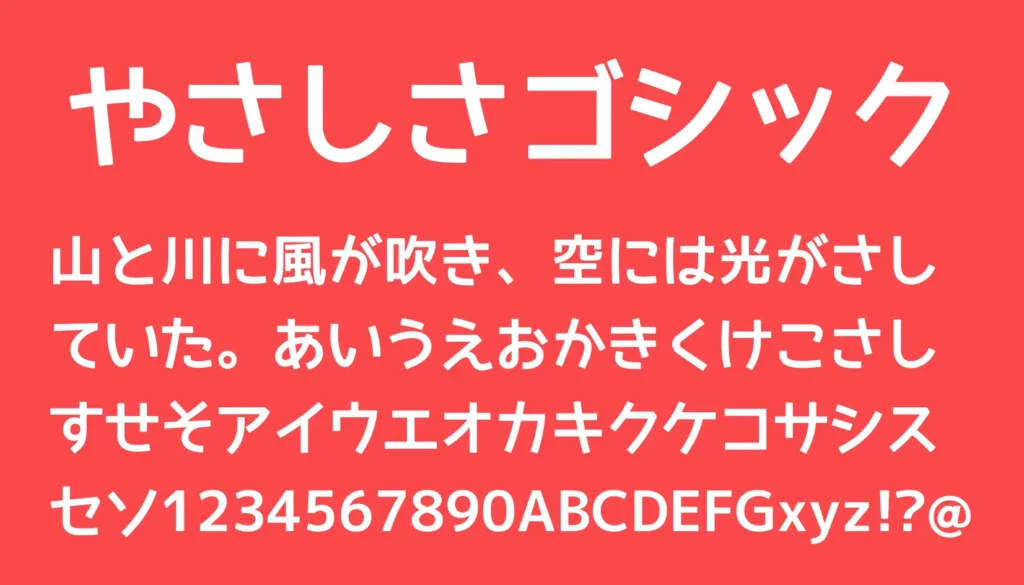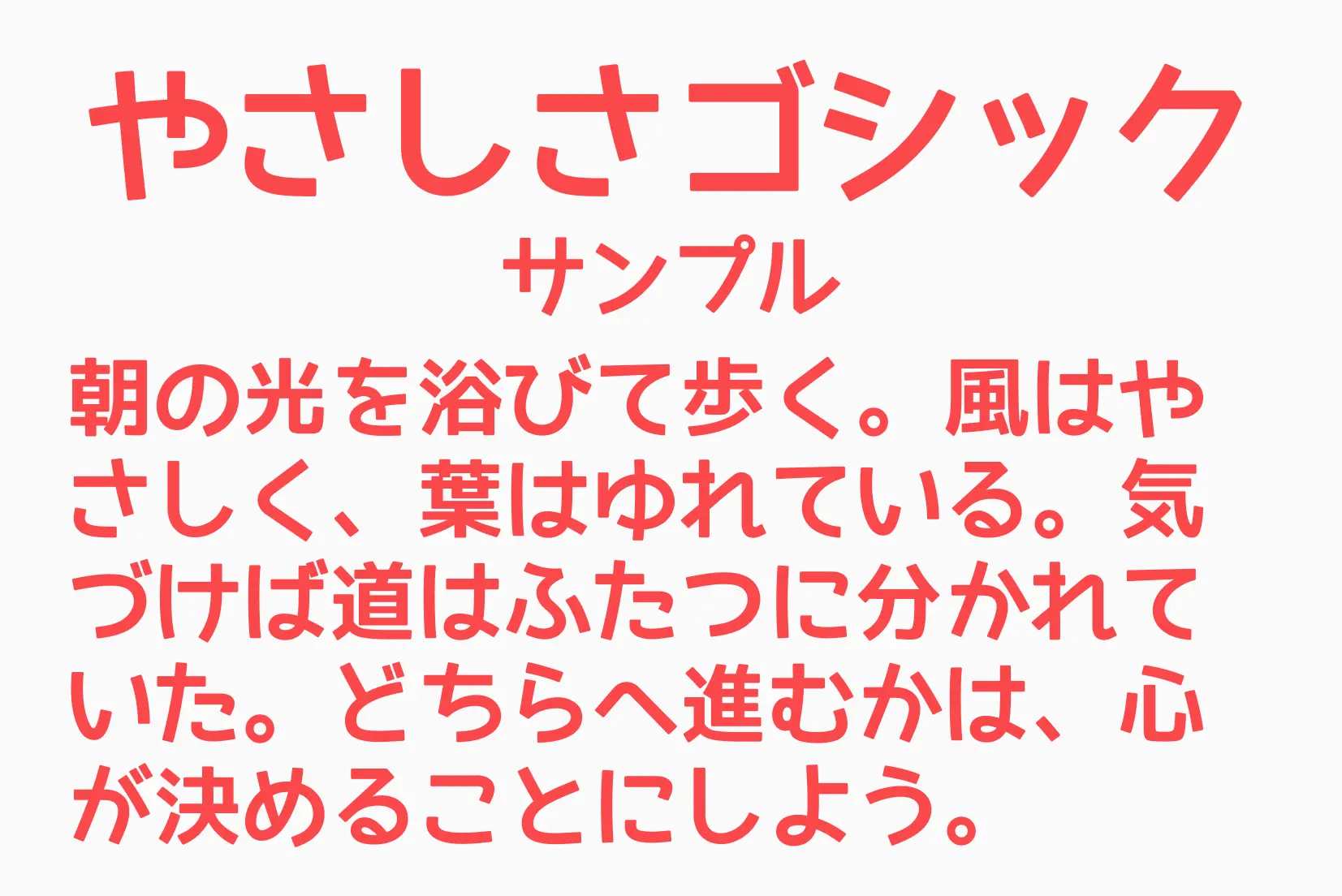
ゴシック体をベースにしながら、ほんのり手書き風のニュアンスを取り入れたやわらかい印象のフォントです。直線的なゴシックに比べて丸みや揺らぎがあり、親しみやすく堅苦しさを感じさせないのが特徴。可読性も高く、本文から見出しまで幅広く使えるバランス型で、子ども向けややさしい雰囲気のデザイン、資料やプレゼンなどにも適しています。
やさしさゴシック